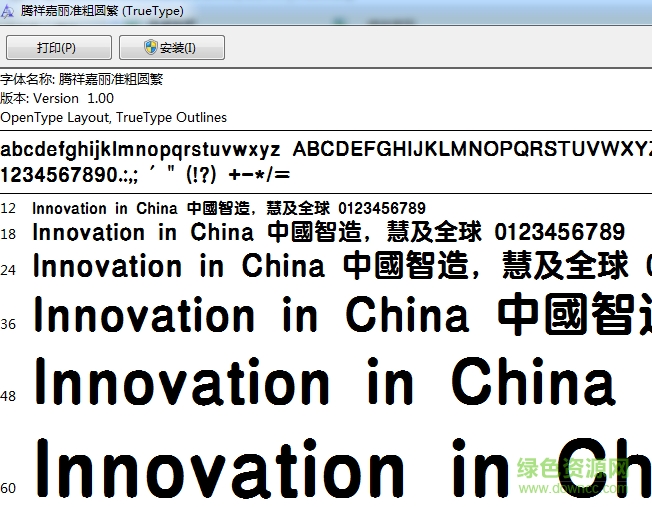
騰祥嘉麗準(zhǔn)粗圓繁體
騰祥嘉麗準(zhǔn)粗圓字體是一款騰祥字體庫中的個性繁體字體,字體非常粗,線條格局非常具有個性,讓用戶能夠靈活使用。有需要的朋友可以來綠色資源網(wǎng)免費下載使用!
騰祥嘉麗準(zhǔn)粗圓字體
騰祥嘉麗準(zhǔn)粗圓字體是一款騰祥字體中的個性繁體字體,精彩的特色設(shè)計滿足多方面需要,有需要的朋友就趕快來綠色資源網(wǎng)下載吧!